自分の好きな文字やかわいい文字を見るとテンションが上がったりしませんか? スマホのフォントを変えている方もいるかもしれません。
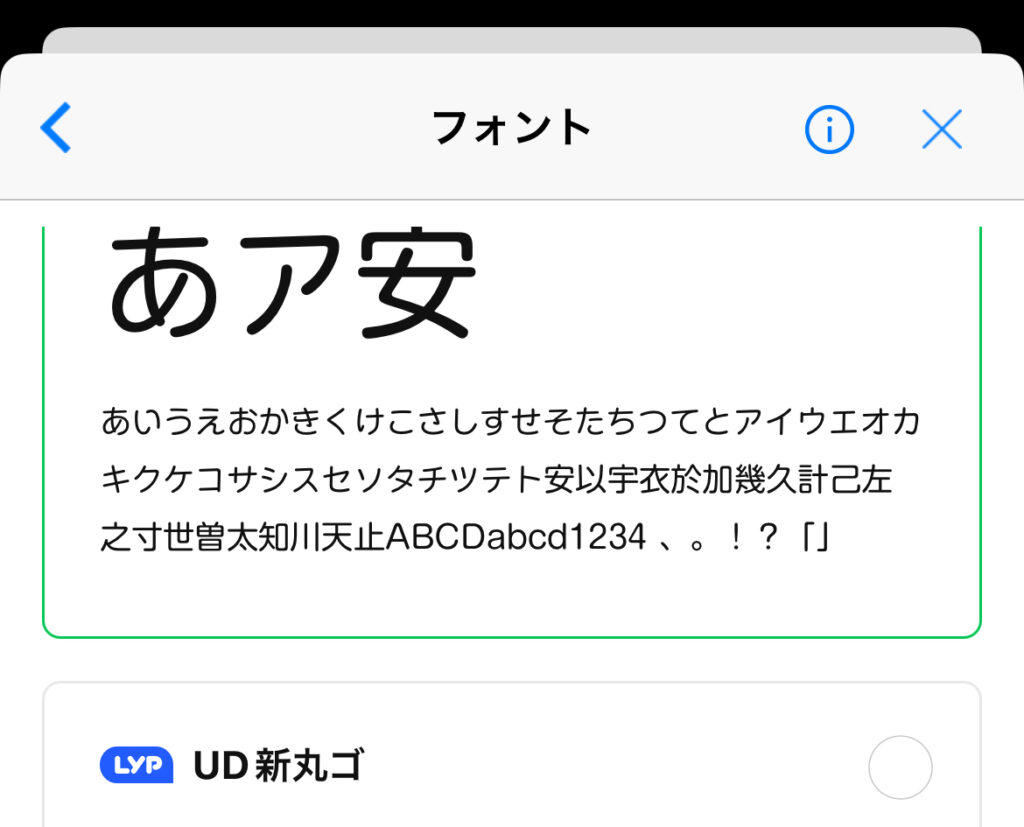
今回はLINEのフォントの変え方を解説します!できない場合の対処法も解説していますので、ぜひ参考にしてみてください!
LINEのフォント変えられるの知ってた?
LINEのフォントが変更できることはご存知ですか? Androidでは以前から端末設定で変えられました。
iPhoneでは以前変えられなかったのですが、2018年5月にリリースした「LINE Labs」の機能で変更できるようになりました。
LINEのフォントを変えるメリット・デメリット
下のように、Twitterでもフォントを変えてテンション上がってる方がいらっしゃいますね!
LINEのフォントを変えるメリット・デメリットについて、説明します。
Twitterなどのコメントを見てみると、下のようなメリット・デメリットが考えられます。
メリット
- テンションが上がる
- アイチャクがわく
- 見やすい
デメリット
- 読みづらい
- 文字化けする
見づらくて元に戻したという意見もあります。普段使っているフォントと違うと、見づらさを感じるかもしれません。
フォントの種類は全部で14種類あります。いろんな種類があるので、見やすいものが見つかるかもしれません。いろいろ試してお気に入りのものを探してみてくださいね。
文字化けする場合は、デフォルトのフォントに戻すと戻るようです。すぐ変更できるので1度やってみるといいでしょう。
LINEフォントの変え方
それではLINEフォントの変え方を説明します。
iPhoneとandroidで設定方法が異なります。それぞれ解説していますので参考にしてください。
人気のおすすめLINEフォントはどれ?
どのようなフォントが人気なのでしょうか? Twitterで、「LINE フォント おすすめ」で検索してみました。
いろんなフォントが出てきましたが、iPhoneの場合はピクセル・エムプラス12を上げている方が多かったです。ゲームみたいで面白いですよね。
下に、それぞれのフォントを画像付きで載せてるので、参考にしてみてください!
iOSのカスタムフォントは14種
iPhoneのフォントは全部で14種類あります。それぞれどのようなものがあるのでしょうか? 下に並べます。